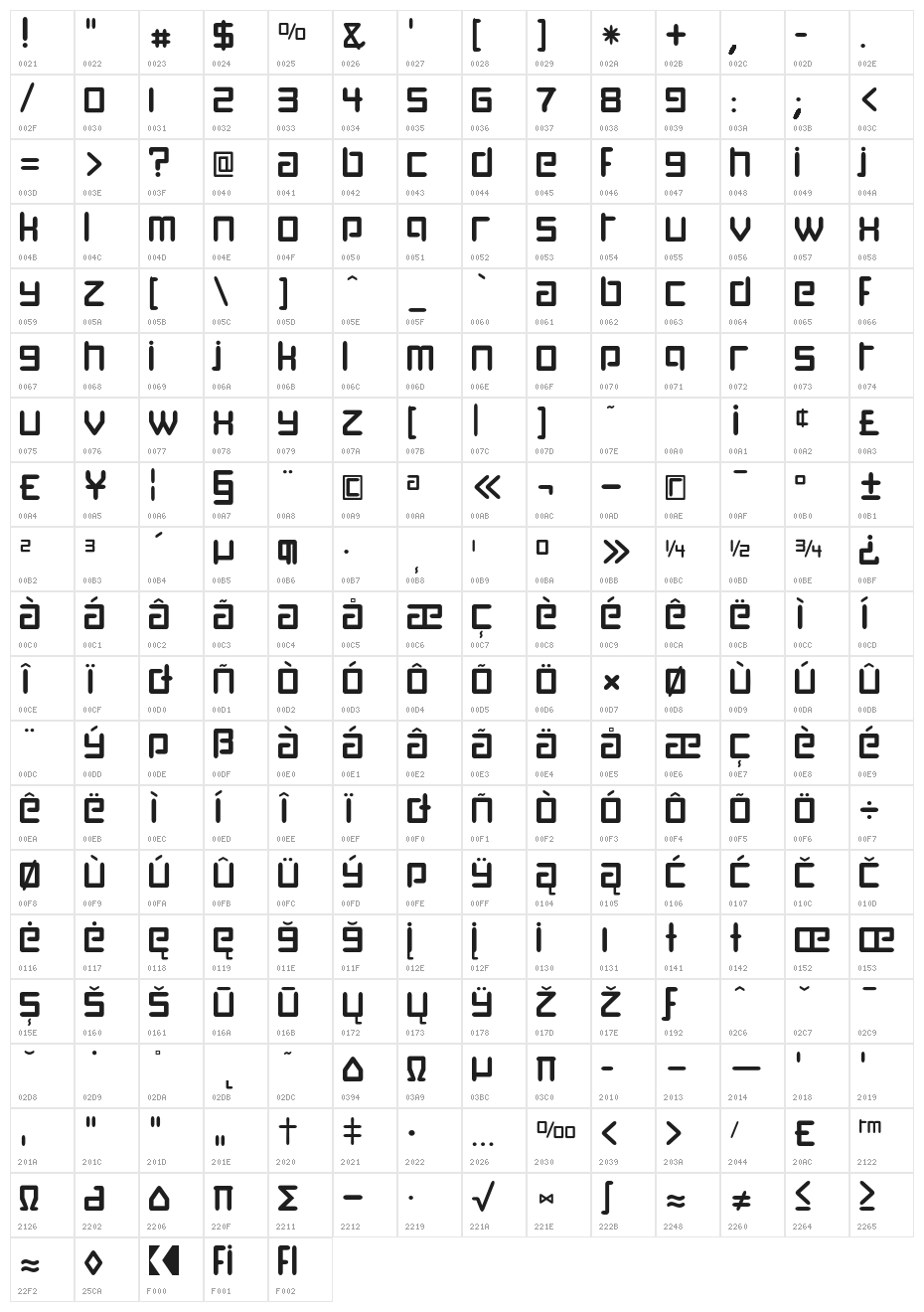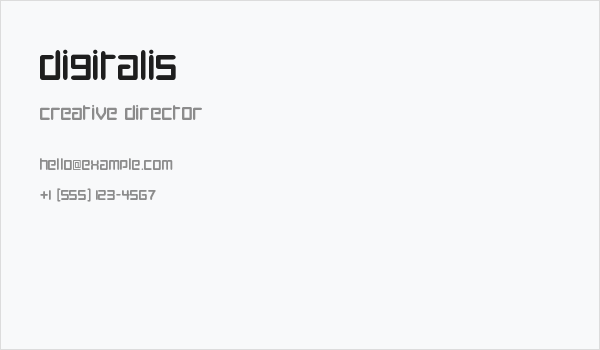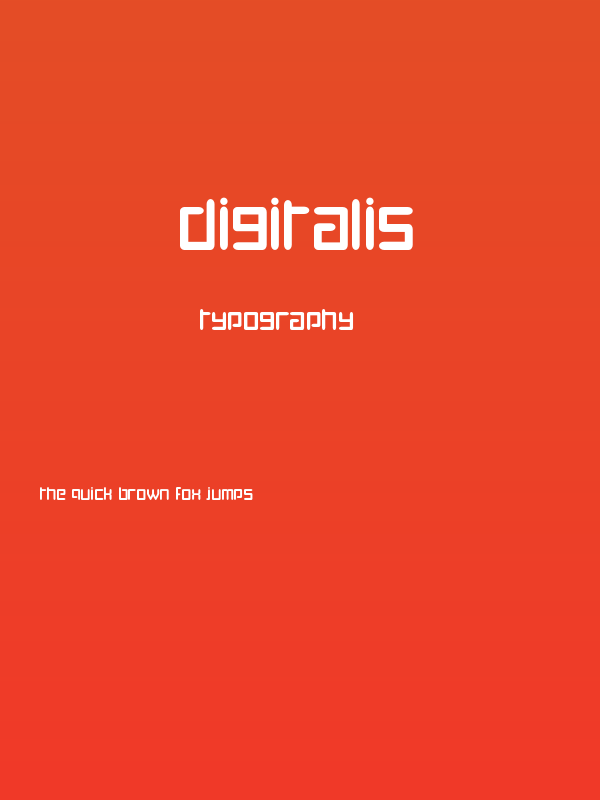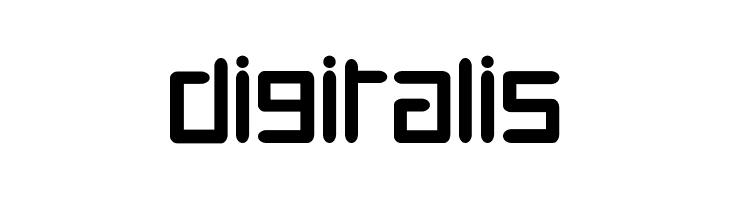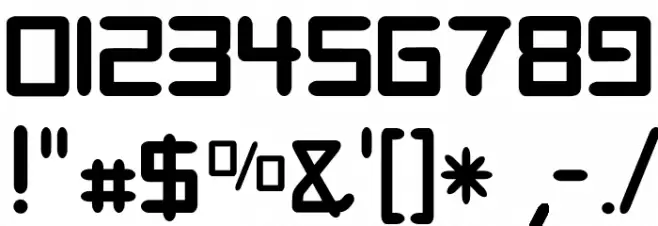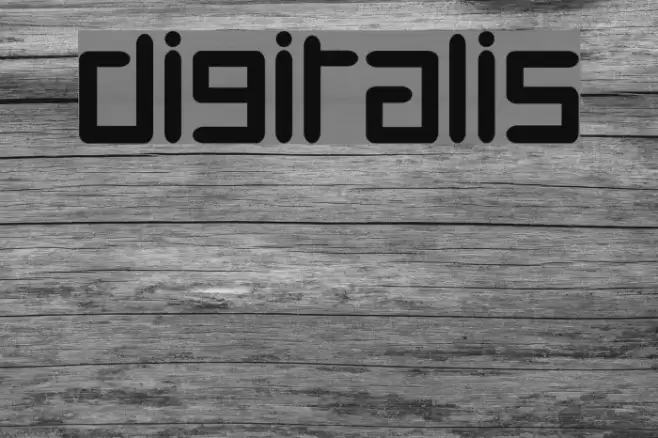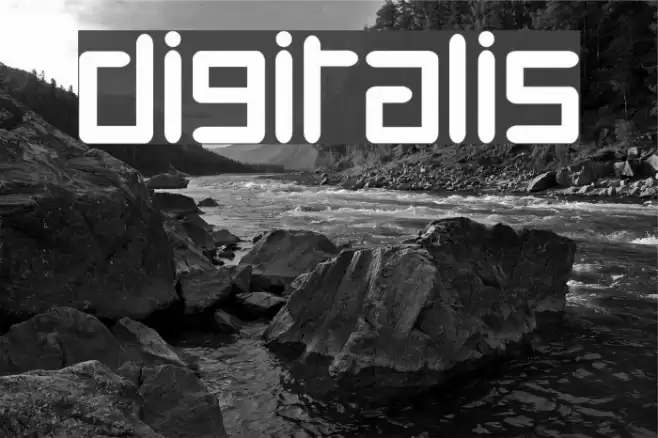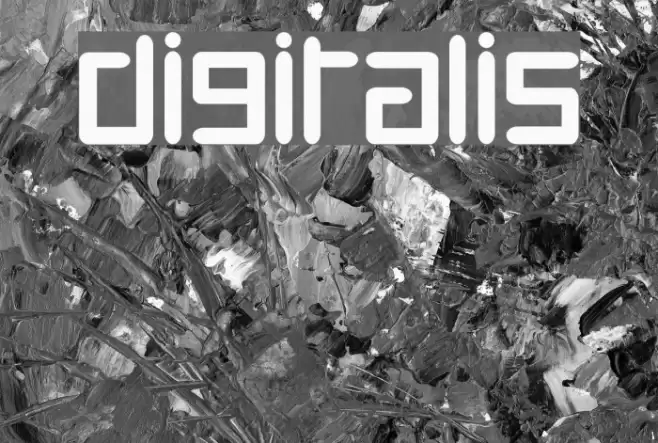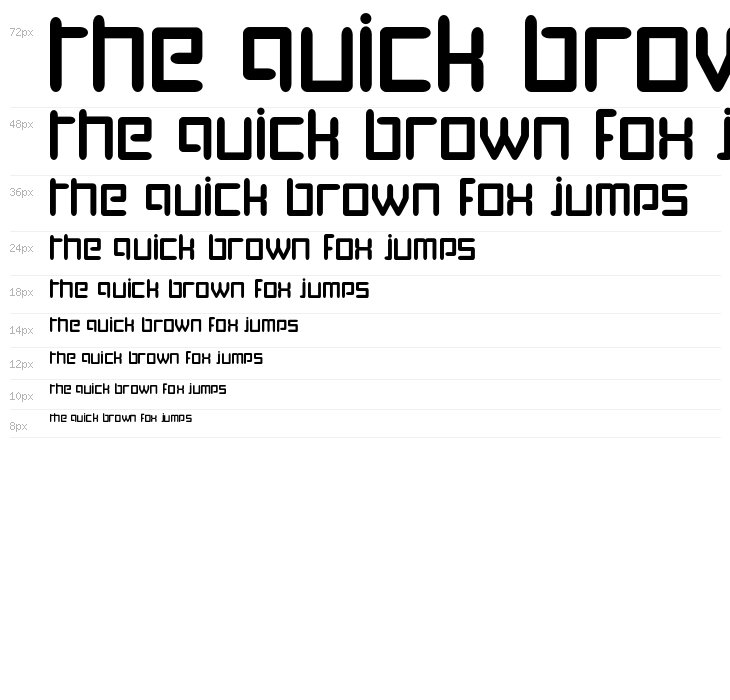
Digitalis Font
| 用途 | Headlines, Logos, Digital Interfaces |
| おすすめプロジェクト | Ideal for technology branding, futuristic posters, digital interfaces, and modern advertising campaigns. |